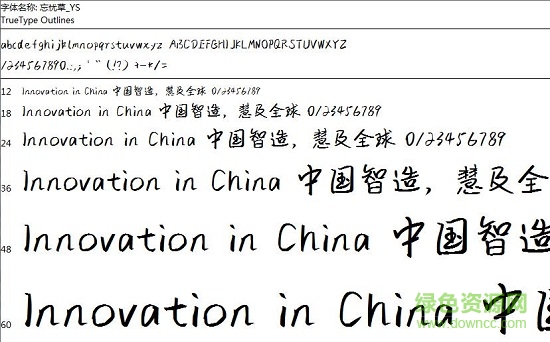
qq空間忘憂草字體
忘憂草網(wǎng)絡(luò)字體簡(jiǎn)介
忘憂草網(wǎng)絡(luò)字體是一款根據(jù)qq中的字體提取出來(lái)的,是一款風(fēng)格獨(dú)特的手寫(xiě)字體,這款字體最大的特色就是連筆連的非常的好看,適合用來(lái)進(jìn)行大面積的排版!
忘憂草網(wǎng)絡(luò)字體